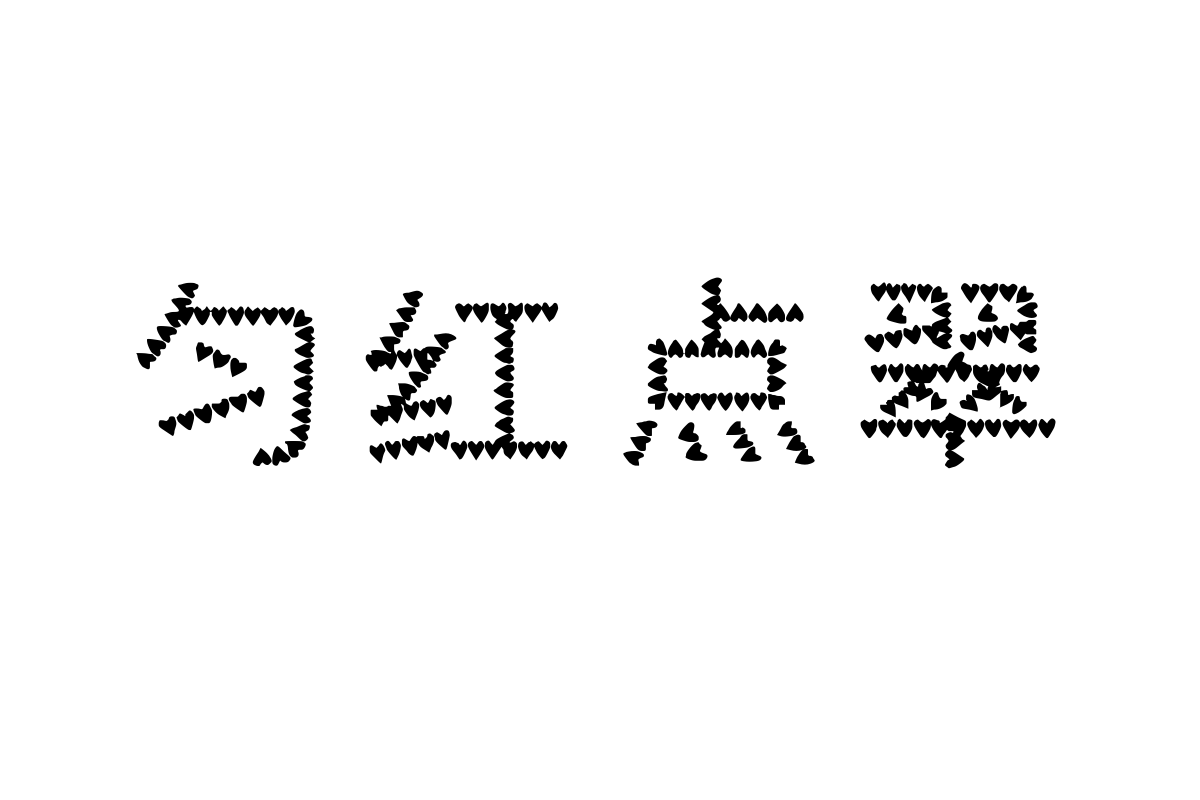
汉标爱心体是一种中文字体,由汉仪公司设计。这种字体具有独特的设计风格,以爱心形状为特点,给人以温馨、亲切的感觉。
汉标爱心体的字体特点是:
1. 字形独特:汉标爱心体采用了爱心形状的笔画,使得整个字体看起来更加可爱、有趣。
2. 易读性强:由于字形独特,汉标爱心体在阅读时不会与其他字体混淆,提高了阅读体验。
3. 适用范围广:汉标爱心体适用于各种场合,如广告、宣传、包装等,具有较强的实用性和美观性。
4. 个性化:汉标爱心体可以根据需要进行个性化定制,满足不同用户的需求。
总之,汉标爱心体是一种具有独特设计风格的中文字体,适合用于需要表达温馨、亲切情感的场合。